De typoboys van Underware hebben de afgelopen jaren veel interessante experimenten met variable fonts gelanceerd. Die losse projecten komen nu samen in wat zij noemen de volgende stap in de evolutie van typografie. Tikkie pretentieus, maar rete interessant.
Ze doopten hun ding Grammatografie en het combineert de voordelen van drie technieken: gezette tekst (typografie), handschrift en variable fonts.
Leer de opbouw van letters
Dit is het ding: schrijven gaat niet alleen over gedachten onder woorden brengen, maar ook over expressie, bijvoorbeeld door handschrift. En persoonlijke expressie zijn we steeds meer aan het kwijtraken in ons schrift. Bij handschrift zit er eerst tekst in je hoofd en pas wanneer je het opschrijft ontstaat de letter. Bij typografie is dat andersom: de letters zijn er al en pas wanneer je typt ontstaat er tekst.
Grammatografie wil de voordelen van gezette tekst (efficiënte distributie) en die van handschrift (persoonlijke expressie) combineren, en doet dat door letters te animeren. Niet door traditionele animatie maar met variable font-technologie. Een aantal usecases vind je op de projectwebsite.
Het concept prikkelt me enorm en ik ben vooral benieuwd naar toepassingen die echt interactief zijn en die de persoonlijke expressie van de gebruiker vergroten ipv die van de letterontwerper.
Future is written.
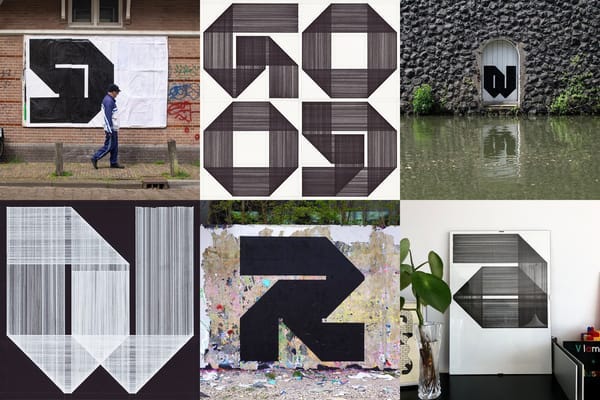
Nespor in het wild
Daan Rietbergen experimenteerde jarenlang met lijnen, grid en witruimte en dat resulteerde in NESPOR, een super dik lettertype dat voelt als een 2D sculptuur. It's Nice That interviewde 'm.
Must listen
Betrouwbare Bronnen met PG Kroeger – Sinds hem ken ik niet meer mijn politieke kleur. In deze spannende angstige tijd zorgt hij voor prachtig inhoudelijk voer. Wel de tijd nemen: duurt 2 uur plus.
Must see
Diego Maradona (documentaire van Asif Kapadia) – Ik was te jong voor Cruyff en ben veel te oud voor CR7. Maradona dus. Sorry dames: de grootste genie ooit is een man (en nr 2, 3 en 4 ook) en ik durf te stellen dat juist de grootsheid aan hem voorbij gaat aan wat hij was: de meest briljante voetballer ooit. De docu is prachtig samengesteld. Zonder typische voice-over die al het materiaal bij elkaar tracht te brengen. Het is ook niet nodig. Zonder die derde persoons-hoek kom je er juist helemaal in en wordt je deel ipv toeschouwer.
Must use
Lynstone typeface – Het zal de leeftijd wel zijn maar het begrip VAN DEZE TIJD neem ik steeds vaker met een beetje lucht. Zonder er afbreuk aan te doen (want je wilt natuurlijk geen ouwe lul zijn) probeer ik er iets aan toe te voegen: VAN ALLE TIJDEN. Gewoon echt goed dus en geen instant pastiche die doet alsof het authentiek is. De Lynstone hebben we gebruikt voor de restyling van de Balie. De letter is een prachtig vervolg op de Gill Sans en zal niet snel vervelen. Ze is modern maar ook romantisch. Een font die verschillende ’tijdsbegrippen’ bij elkaar brengt en dat doet de Balie juist ook: ze zit in het hier en nu, maar praat over de toekomst en haalt uit het verleden.
Stephan is mede-oprichter van Van Lennep Design Agency
Email Love verzamelt email design inspiratie.
Sketchsheets zijn Sketch-templates van verschillende devices om uit te printen en op te schetsen.